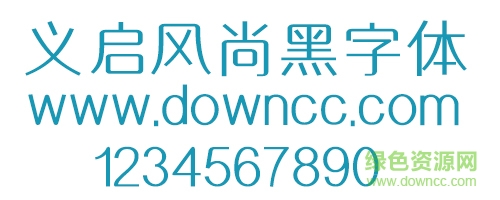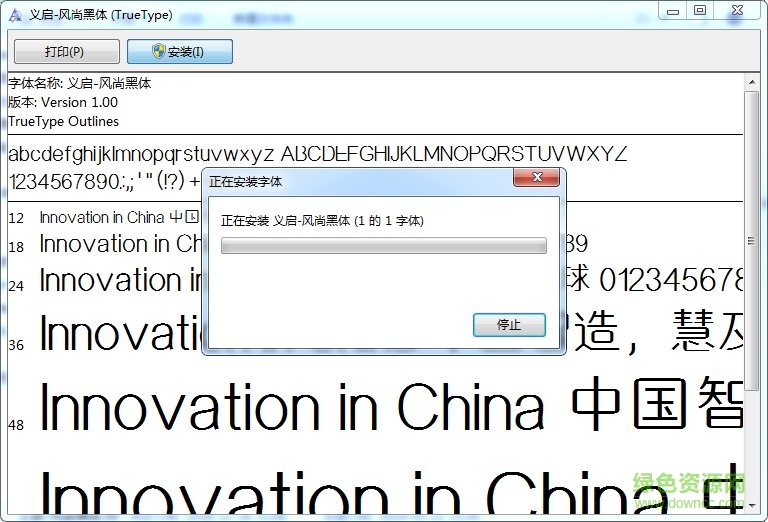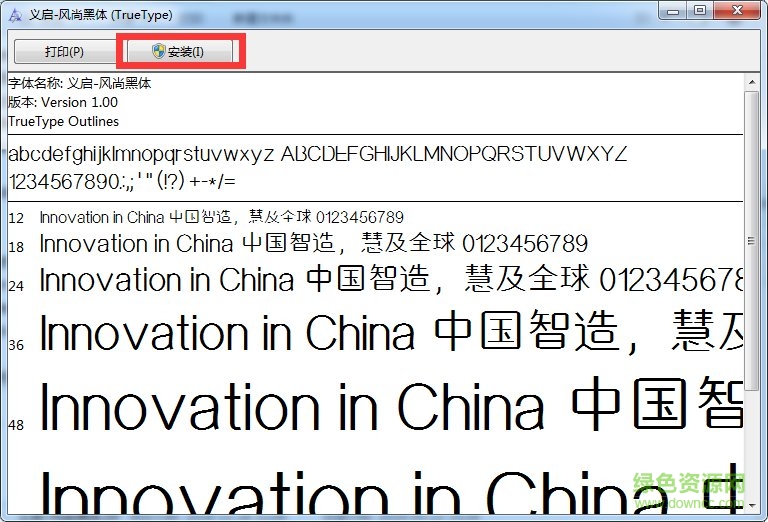
義啟風尚黑字體是一個免費的設(shè)計字體資源。輸出的內(nèi)容非常規(guī)范大方。可以用來設(shè)計海報、宣傳冊等。支持漢字、英文、數(shù)字輸入,兼容多種操作系統(tǒng)!歡迎在綠色資源網(wǎng)下載使用。
義啟風尚黑字體效果中規(guī)中矩,字形端正,字庫完整,能夠應(yīng)用于文本裝潢、信息展示、網(wǎng)頁設(shè)計、篆刻制模、數(shù)據(jù)制作、裝潢設(shè)計、計算藝術(shù)設(shè)計、視覺設(shè)計、字帖等場景!
中文名稱:義啟-風尚黑體
英文名稱:iekie-fengshangheiti
字體分類:中國大陸/義啟/綜藝體/精致綜藝